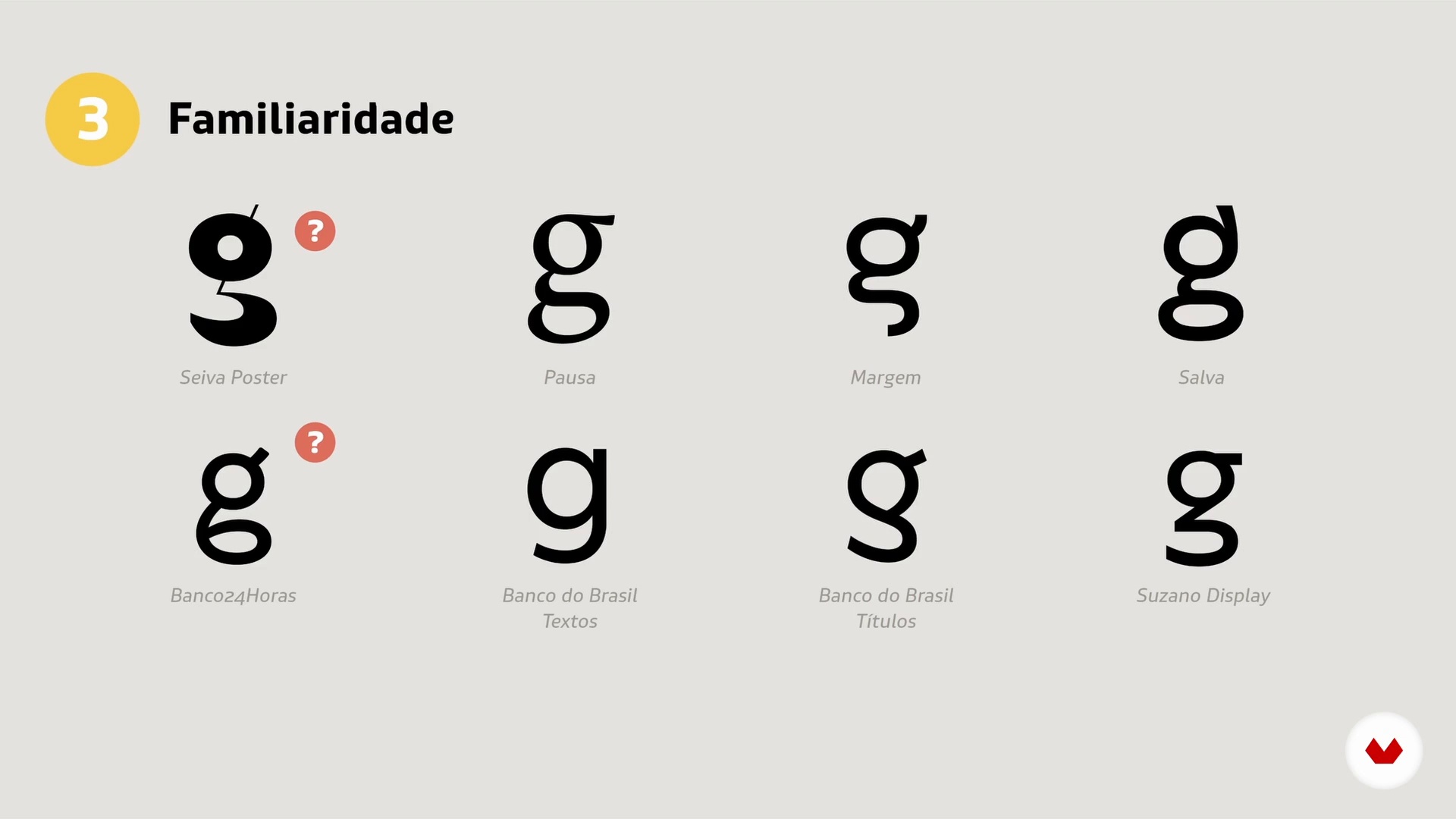
Lesbarkeit und Lesbarkeit in der Praxis
Über die Videolektion: Lesbarkeit und Lesbarkeit in der Praxis
“Hier erfahren Sie in der Praxis, wie wir aktuelle wissenschaftliche Erkenntnisse auf typografische Entscheidungen in unserem täglichen Leben anwenden.”
In dieser Videolektion behandelt Fabio Haag das Thema: Lesbarkeit und Lesbarkeit in der Praxis, das Teil dieses Domestika-Onlinekurses ist: Typografie für den Aufbau wertvoller Marken. Entdecke die Macht der Typografie bei der Schaffung eines wertvollen und effektiven Markenauftritts. Lerne, wie du fundierte typografische Entscheidungen treffen kannst..
Partielle Transkription des Videos
“Schauen wir uns nun in der Praxis einige Funktionen an, die die Lesbarkeit von Typografie erleichtern. Offene Enden und weite Gegenformen. Wenn die Enden sehr geschlossen sind, sogar Menschen mit ein wenig Schwierigkeiten Vision kann Buchstaben wie C verwirren, Ö, E und A zueinander. Es ist wichtig, dass diese Formen sehr unterschiedlich sind. Offene Enden machen das einfach, zusätzlich zur Vergrößerung des Innenbereichs, die Gegenform, der negative Raum der Buchstaben, Dadurch wird die einzigartige Form jedes Buchstabens deutlicher. Ein zweiter Punkt, Vermeiden Sie die üblichen Betrüger. W...”